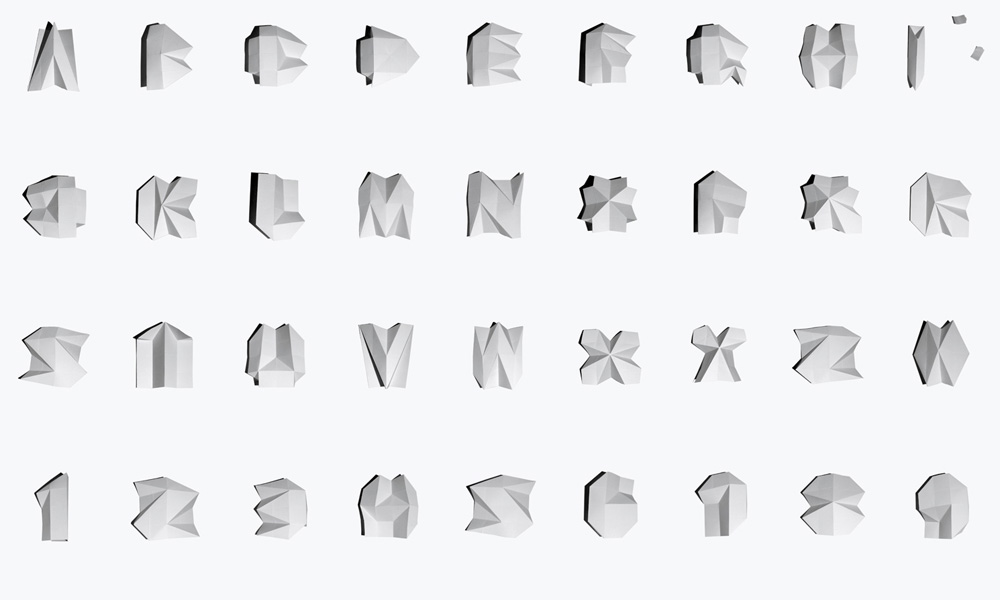
Die Berliner Galerie im Turm zeigt ab 3. August unter dem Titel Typosphäre eine Ausstellung zu aktuellen Positionen der Typografie und Kalligrafie, mit acht verschiedenen Künstlern aus drei verschiedenen Ländern (Taiwan, Frankreich und Deutschland). Die Ausstellungseröffung ist am 2. August ab 19 Uhr, das Begrüßungswort wird Dr. Wu-Lien Wei, Repräsentant Taipeh Vertretung in der Bundesrepublik Deutschland sprechen. Gefördert wird die Ausstellung vom Centre Culturel de Taiwan in Paris.
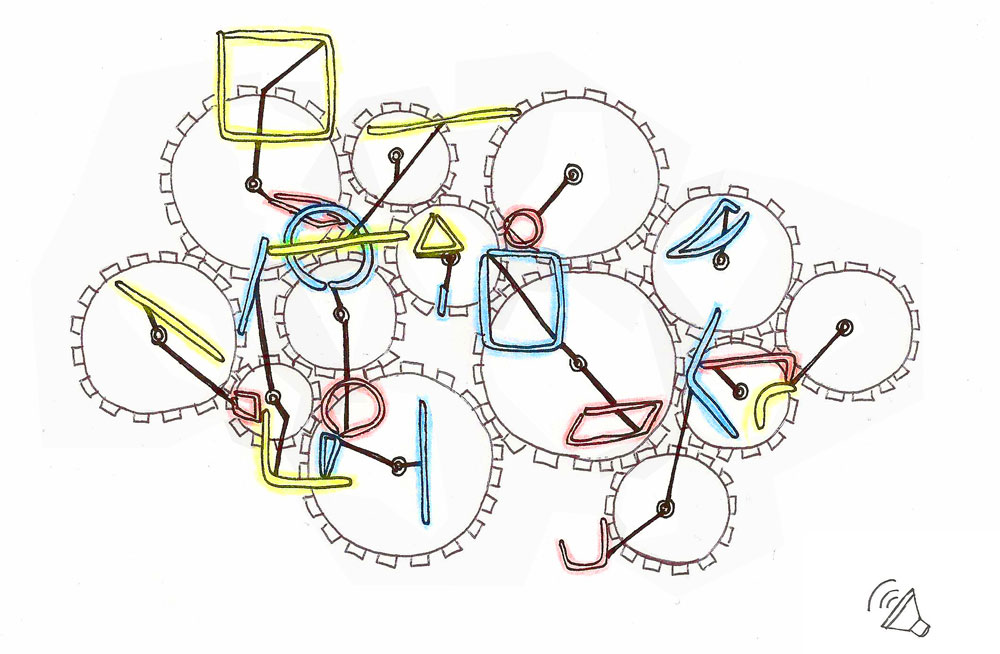
Die ausgestellten Werke beschäftigen sich mit chinesischen und lateinischen Schriftformen, die geschrieben oder gedruckt sind. Sie stoßen einen Dialog an zwischen Kalligrafie und Typografie sowie zwischen Zeichnung und Druck. Anne Mundo zeigt in abstrakten Zeichnungen ihr Verständnis über die Nuancen zwischen dem Kalligrafischen und dem Zeichnerischen. Alexander Behn präsentiert seine Buch- und Buchstabenobjekte, um seine gestalterische Auseinandersetzung mit den physischen und haptischen Qualitäten von Lettern darzustellen. Bo-Cheng Shen demonstriert in einer Blindenschrift-Klanginstallation das grenzenüberschreitende Zusammenwirken von visuellen, akustischen und haptischen reizen. Die Tamtam Art Group beschäftigt sich in ihrer Licht-Klang-Installation mit dem Zusammenhang zwischen Sprache und Stimme sowie zwischen Schrift und Bild. Chieh-Ting Hsieh übersetzt chinesische Notationen in seine musik. Weiterhin zeigt die Ausstellung Typo-Poesie von Julienne Jattiot, kalligrafische Comics von Sebastian Russek und eine Lese-installation von Yung-Shan Tsou.